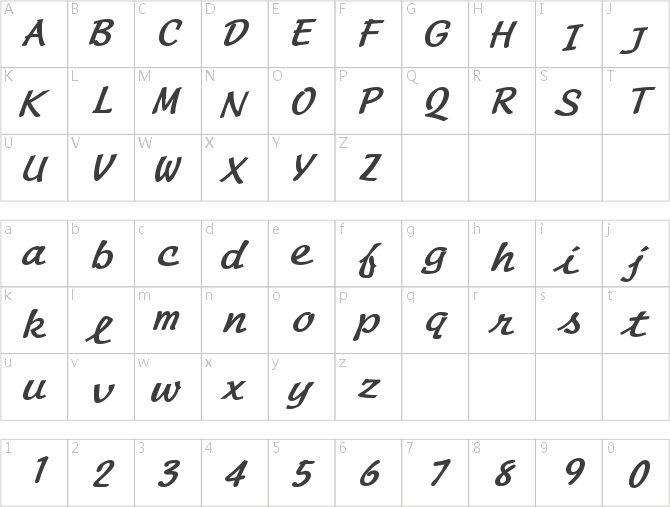
Manuscript-Wide-BoldItalic 詳情頁
Manuscript-Wide-BoldItalic
Manuscript-Wide-BoldItalic介紹
Manuscript-Wide-BoldItalic字體字庫是一款讓人賞心悅目、百看不厭的英文字體,適合各類廣告和產品包裝設計應用,字體大小0.07MB,格式為ttf字體,上傳用戶是翰池書法,作者/版權方為未知